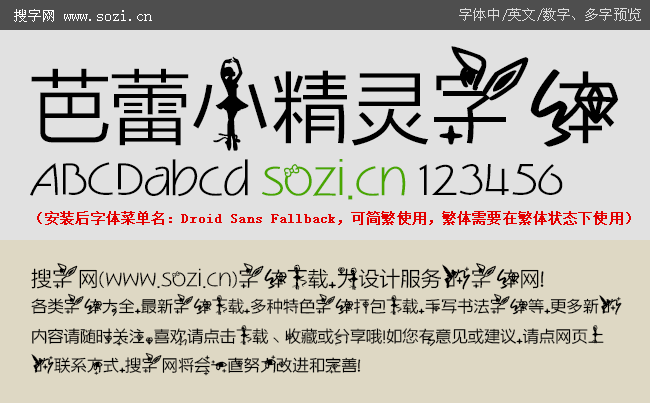
芭蕾小精靈字體
搜字網(wǎng)給大家提供一款芭蕾小精靈字體手機(jī)中文字體下載。這款手機(jī)字體是以黑體字體為原形,個別字體筆畫間嵌入了卡通圖案。在具備黑體清晰端正的風(fēng)格同時,卡通味也特別濃,是一款很有趣的卡通字體,特別適合喜歡手機(jī)字體個性一些的朋友在手機(jī)上安裝使用。